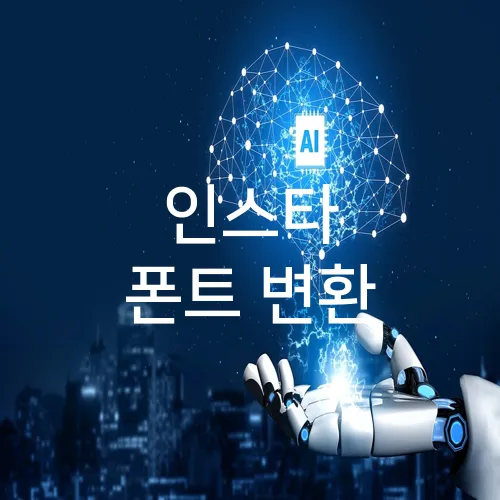
1. 인스타 폰트 변환: 손글씨 느낌의 따뜻한 스타일
인스타 폰트 변환의 중요성
소셜 미디어 플랫폼인 인스타그램에서는 시각적 콘텐츠뿐만 아니라 텍스트가 중요한 역할을 합니다. 인스타 폰트 변환은 브랜드의 고유한 개성을 표현하는 데 큰 도움을 줍니다. 다양한 폰트를 활용하면 게시물의 주목성을 높이고 팔로워의 참여도를 한층 더 끌어올릴 수 있습니다.
손글씨 느낌의 따뜻한 스타일
손글씨 느낌의 폰트는 따뜻함과 개성을 전달하는 데 탁월합니다. 특히, 개인적인 감성이나 메시지를 전하려는 포스팅에서 유용하며, 팬들과의 소통을 매끄럽게 해줍니다.
– `Cursive`나 `Pacifico`와 같은 폰트는 부드럽고 유연한 느낌을 주어 사람들에게 친근함을 느끼게 합니다.
– `Calligraffitti` 폰트는 마치 손으로 직접 쓴 듯한 필기체 스타일을 제공하여 특별한 분위기를 연출할 수 있습니다.
이런 스타일은 쿠팡의 책 리뷰 페이지나 네이버 블로그에서 개인적인 리뷰를 작성할 때 흔히 사용되며, 자신의 생각이나 기분을 따뜻하게 표현하는 데 좋습니다. 최근 인스타그램에서는 일상적인 소통에서도 인스타 폰트 변환을 활용하여 더 많은 주목을 받고 있습니다.
손글씨 스타일을 사용할 때 고려할 점
폰트를 선택할 때는 다음 요소들을 고려하세요:
– 읽기 쉬움: 아무리 멋진 스타일이라도 읽기 어려우면 효과가 반감됩니다.
– 일관성: 다른 스타일과 혼합하기보다는 통일감을 주는 것이 중요합니다.
공식 인스타그램 앱에서는 기본적으로 이와 같은 고유한 폰트를 제공하지 않으므로, 외부 애플리케이션이나 웹사이트, 예를 들어 `LingoJam` 등을 통해 손글씨 스타일로 쉽게 변환할 수 있습니다. 이를 통해 다른 사용자와 차별화된 게시물을 쉽게 만들 수 있습니다.
2. 화려하고 눈에 띄는 세리프 폰트 적용법
화려하고 눈에 띄는 세리프 폰트 적용법
인스타그램에서 눈길을 사로잡는 방법 중 하나는 특별한 폰트를 사용하는 것입니다. 그중에서도 세리프 폰트는 글자에 깊이와 클래식을 더해 팔로워들의 시선을 끌기에 적합합니다. 세리프 폰트를 사용하면 회원님만의 독특한 개성을 표현할 수 있습니다.
세리프 폰트를 인스타그램에 적용하는 방법은 다양합니다. 먼저, ‘Cool Fonts’와 같은 앱을 사용하여 원하는 세리프 스타일을 선택할 수 있습니다. 이 앱은 다양한 폰트 스타일을 제공하므로 개인의 취향에 맞는 폰트를 쉽게 찾아 적용할 수 있습니다.
– Web사이트 ‘Lingojam’: 직접 텍스트 입력 후 변환 결과 확인 가능
또한, Canva와 같은 디자인 플랫폼을 활용하는 방법도 있습니다. Canva에서는 셀프 커스터마이징이 가능하여, 게시물 전체의 디자인에 맞게 폰트를 조정할 수 있습니다. 특히 사용자가 직접 다양한 요소를 추가하여 원하는 레이아웃을 디자인할 수 있는 것이 큰 장점입니다.
세리프 폰트의 매력은 가독성에도 있습니다. 글자에 작은 곡선과 장식 요소를 추가하여, 텍스트의 흐름을 한층 매끄럽게 만들어 줍니다. 이는 특히 긴 문장을 작성할 때 유용합니다.
– 장점: 가독성 높임, 다양한 커스터마이징 가능
인스타그램에서 이러한 폰트를 사용하면 브랜드 이미지 고급화 및 팔로워에게 강렬한 인상을 심어줄 수 있습니다. 각기 다른 플랫폼과 앱을 활용하여 자신의 스타일에 맞는 세리프 폰트를 찾아보시기 바랍니다. 다양한 옵션과 방법을 활용하여 더욱 매력적인 인스타그램 피드를 완성할 수 있습니다.
3. 인스타 폰트 변환을 통한 모던한 미니멀리즘 표현
모던 미니멀리즘의 매력
인스타그램에서 폰트 변환은 단순한 텍스트를 독창적이고 매력적으로 변신시키는 강력한 도구입니다. 특히 미니멀리즘을 추구하는 사용자들에게는 더욱 유용합니다. 깔끔하고 정돈된 글씨체는 단순함을 강조하면서도 세련된 이미지로 보일 수 있습니다.
모던한 미니멀리즘 표현을 추구할 때 사용하는 인기 있는 방법 중 하나는 산세리프(sans-serif) 스타일입니다. 예를 들어, Arial이나 Helvetica와 같은 폰트는 간결하면서도 현대적인 느낌을 제공합니다. 이 폰트들은 주로 명료한 브랜드 이미지와 일관성 있는 피드를 유지하는 데 효과적입니다.
인스타그램에서 폰트 변환 적용하기
폰트 변환을 쉽게 적용할 수 있는 방법 중 하나는 다양한 온라인 도구를 활용하는 것입니다. Lingojam이나 Cool Symbol과 같은 웹사이트는 사용자가 다양한 폰트를 손쉽게 선택하고 적용할 수 있도록 지원합니다.
이러한 도구는 사용자 인터페이스가 직관적이며, 몇 번의 클릭만으로 원하는 폰트 스타일을 미리 볼 수 있는 기능을 제공합니다. 각 도구는 특별한 폰트 스타일을 제공하며, 변환된 텍스트를 바로 인스타그램 등 소셜 미디어에 복사해 넣을 수 있습니다.
폰트로 미니멀리즘에 생명 담기
인스타그램에서 모던하고 미니멀한 느낌을 극대화하고자 할 때, 색상과 레이아웃에도 신경 써야 합니다. 흑백의 대비가 극명한 폰트는 시각적으로 눈에 잘 띄고, 간결한 캡션과 조화를 이루어 피드의 전체적인 조화를 유지합니다.
또한, 충분한 여백을 활용하여 텍스트가 혼잡해 보이지 않도록 하는 것도 중요합니다. 적절한 여백은 미니멀리즘을 더 돋보이게 하고 독자들의 읽기 경험을 향상시킬 수 있습니다. 이러한 요소들은 미니멀리즘을 지향하는 포스트에 필수적입니다.
인스타그램 폰트 변환을 활용한 모던 미니멀리즘 스타일은 단순하면서도 강한 인상을 남깁니다. 이를 통해 팔로워들과 소통할 때 더 깊고 의미 있는 메시지를 전달할 수 있습니다.
4. 복고풍의 레트로 폰트로 트렌디하게 변신
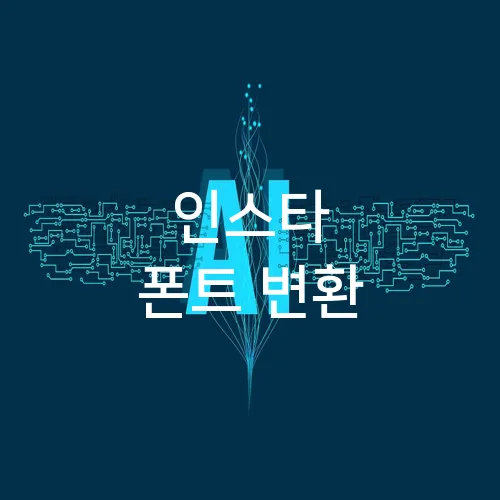
복고풍의 레트로 폰트로 트렌디하게 변신
레트로라는 단어는 이제 더 이상 과거를 의미하는 것에서 그치지 않고, 현재의 트렌드이기도 합니다. 인스타그램에서 눈에 띄고 싶다면 레트로 스타일 폰트로 색다름을 더해보세요.
복고풍 폰트는 70년대와 80년대의 디자인을 현대적으로 해석한 것이 특징입니다. 이 스타일은 그냥 아름답기만 한 것이 아니라, 옛 감성을 불러일으켜 독자들에게 친근감을 줍니다.
대표적으로 ‘Moonhouse Font’나 ‘Chevrette Font’ 같은 폰트가 인기를 끌고 있습니다.
이들 폰트는 굵직하고 선명한 선을 가지고 있어 주목성이 뛰어납니다.
– 이런 폰트를 사용하는 브랜드로는 ‘Urban Outfitters’와 ‘Free People’이 있습니다.
– 제품 설명이나 브랜드 이미지에 레트로 폰트를 사용하여 독특한 분위기를 연출합니다.
따라서, 인스타 피드에 복고풍의 매력을 더하고 싶다면, 이런 폰트를 선택해 보세요. 이는 단지 텍스트를 강렬하게 보이게 할 뿐만 아니라, 브랜드 또는 개인 페이지의 특성을 잘 드러낼 수 있는 좋은 방법이 될 것입니다.
인스타 폰트 변환은 이러한 레트로 스타일을 적용하기 쉽게 도와줍니다. 폴리스타일이나, 폴트 제너레이터 등의 툴을 사용하면 누구든지 쉽게 변환 가능합니다.
– 이렇게 변경된 폰트는 텍스트를 더욱 돋보이게 만듭니다.
– 독자들이 스크롤하다가 멈추게 만드는 매력이 있습니다.
결국, 인스타에서 나만의 스타일을 확고히 하고싶다면 복고풍 폰트를 활용해 보세요. 이는 단순해 보이지만, 상당한 변화를 가져올 수 있는 강력한 도구입니다.
5. 인스타 감각을 살리는 심플하지만 강렬한 산세리프 폰트
산세리프 폰트의 장점
산세리프 폰트는 인스타그램에서 특히 인기 있는 스타일 중 하나입니다. 이 폰트는 깔끔하고 세련된 느낌을 주어 사용자들이 메시지를 보다 명확하게 전달할 수 있도록 돕습니다. 고딕체와 같이 불필요한 장식을 최소화하여 가독성이 높으며, 모바일 환경에서도 눈에 쉽게 들어옵니다.
– 예를 들어, Noto Sans와 같은 폰트는 여러 언어를 지원하면서도 각각의 글자들이 비교적 간결하게 디자인되어 있어 글로벌 사용자에게 적합합니다.
– 또한, 몬세리프(Montserrat) 폰트는 부드러운 곡선과 직선의 조화를 통해 현대적이고 도시적인 감각을 추가합니다.
인스타 감각을 살리는 비결
일반 폰트와는 다른 산세리프 폰트의 매력은 브랜드 이미지에도 긍정적인 영향을 줍니다. 비즈니스 계정이라면 여러분의 브랜드에 맞는 폰트를 선택하여 팔로워들에게 일관된 이미지와 신뢰성을 전달할 수 있습니다.
– Trello의 인스타그램 계정은 산세리프 폰트를 사용하여 팀워크와 프로젝트 관리의 전문성을 강조합니다.
– Airbnb는 브랜드의 최신 트렌드를 반영하기 위해 깔끔한 산세리프 폰트를 사용하여 젊고 창의적인 이미지를 유지합니다.
폰트 선택 시 유의할 점
산세리프 폰트를 선택할 때는 다음과 같은 점을 고려하세요:
– 폰트의 크기와 두께를 조절하여 강조하고자 하는 메시지를 명확히 전달합니다.
– 다양한 배경색과 잘 어울릴 수 있는 중립적인 색상을 선택하는 것도 중요합니다.
폰트 변환 도구를 사용하면 쉽게 여러 스타일을 테스트해볼 수 있습니다. 인스타그램 테마에 맞는 최적의 폰트를 찾아 여러분의 콘텐츠를 돋보이게 만들어보세요.
6. 폰트 변환으로 인스타 피드에 개성 더하기: 결론
인스타그램 폰트 변환의 필요성
다양한 폰트 옵션 맛보기
다양한 폰트 스타일은 브랜드나 개인의 이미지를 반영하는 데 큰 도움이 됩니다. 예를 들어, 대담한 폰트를 사용하여 주목도를 높이거나, 부드럽고 세련된 폰트를 활용해 고급스러움을 더할 수 있습니다. 인스타그램의 독특한 폰트 생성을 지원하는 앱으로는 ‘Fancy Text Generator’와 ‘Stylish Text’가 있으며, 사용이 간편합니다.
사용 시 주의할 점
폰트 변환을 사용하면서 주의해야 할 점도 있습니다. 과도한 폰트 사용은 오히려 가독성을 떨어뜨릴 수 있습니다. 중요한 정보는 기본 폰트를 그대로 유지하여 읽기 쉽게 하는 것이 중요합니다.